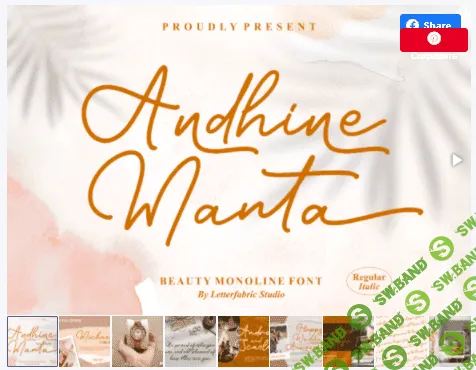
Название: Andhine Manta Beauty Monoline Font (2022)
[creativefabrica] Andhine Manta Beauty Monoline Font (2022)
Andhine Manta — изящный и красивый рукописный шрифт. Он подходит для различных проектов, таких как: логотипы, проекты брендинга, дизайн товаров для дома, упаковка продуктов, кружки, цитаты, плакаты, сумки для покупок и различные другие творения. Andhine Manta имеет кодировку PUA, что означает, что вы можете легко получить доступ ко всем глифам и росчеркам!